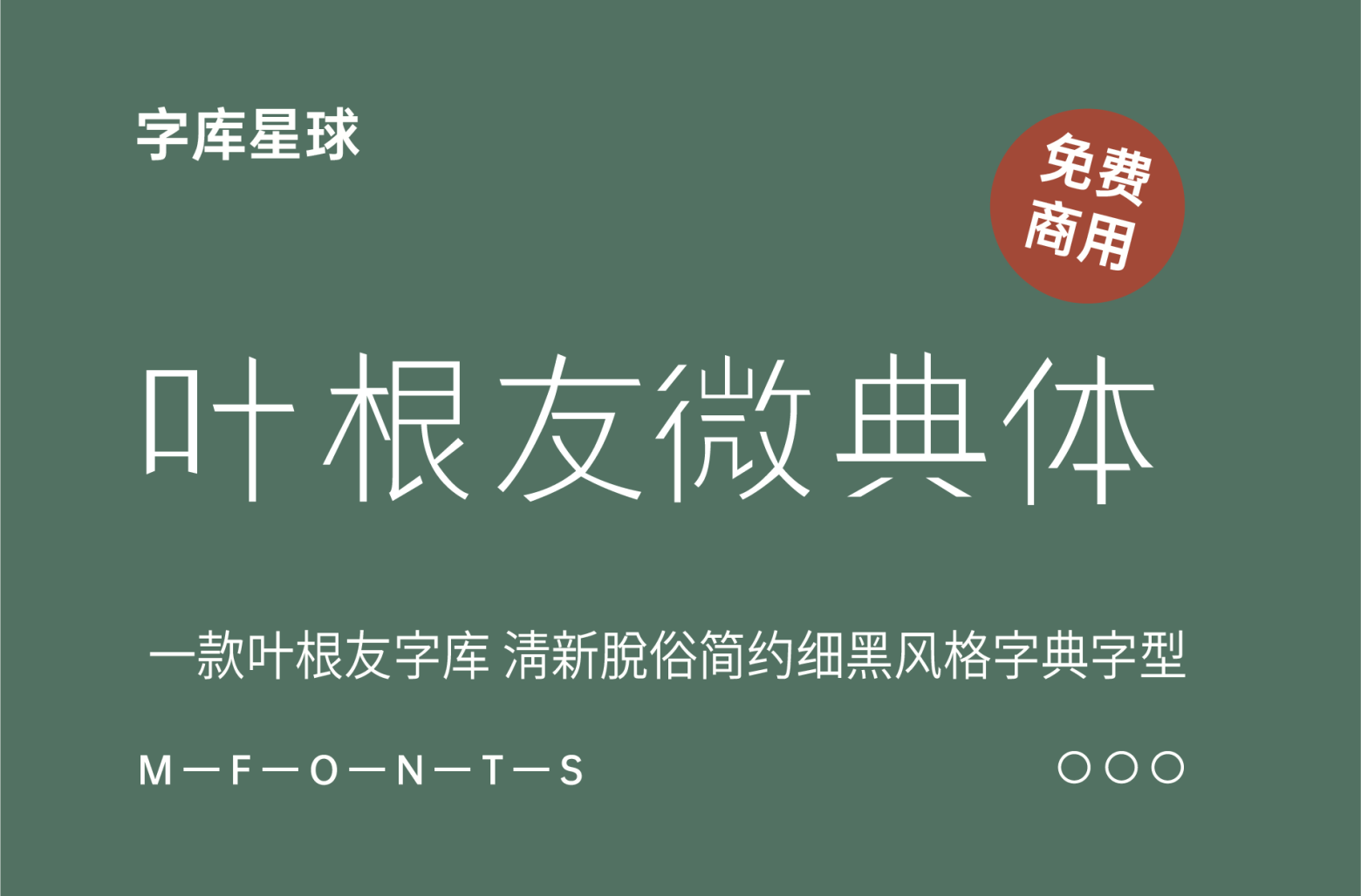
叶根友微典体
从2019年08月01日起,为了感谢各粉丝的支持,我国字体设计师叶根友特别公开四款字体免费商用。这四款字体分别是 叶根友守中曲画、叶根友微典体、叶根友微禅云、叶根友锐劲体。
叶根友微典体是一款简约细黑风格字体。微典体是叶根友字体系统中比较细腻的一款字体,字体笔画犹如发丝,非常清新脱俗。适合平面设计,艺术设计等载体应用。